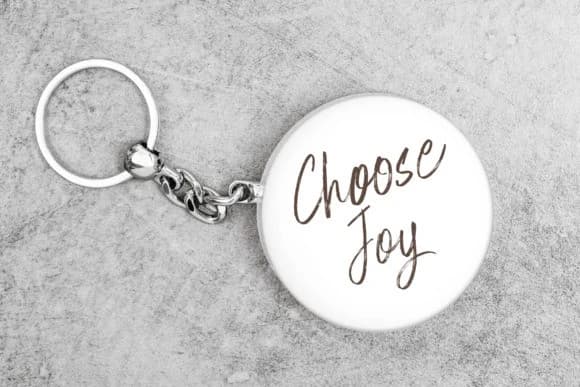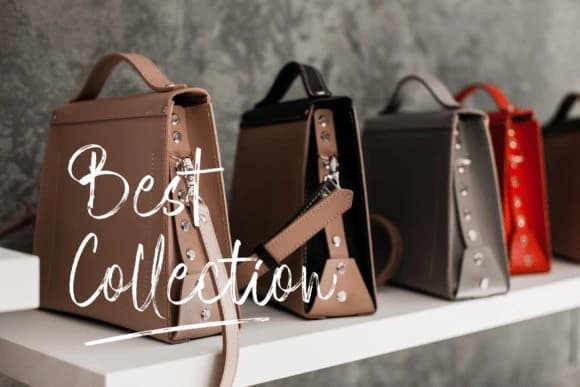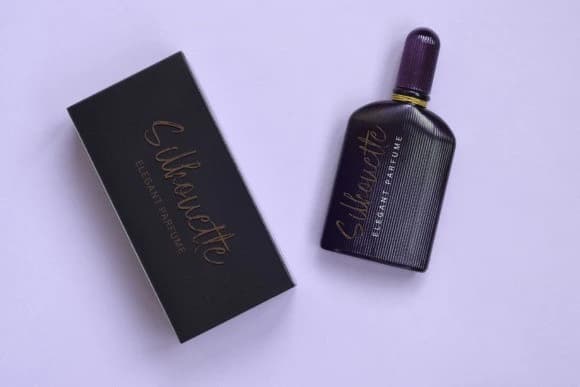
Rettabelle Brush Yazı Tipi
Rettabelle Font – zarifçe rafine edilmiş bir yazı tipi, doğal fırça yazımının cazibesiyle şekillendirilmiş. Romantik estetiği, büyüleyici düğün davetiyeleri tasarlamak, benzersiz marka kimliği oluşturmak, şık logolar tasarlamak ve sosyal medyada etkileyici içerikler üretmek için idealdir.
Rettabelle Font – zarifçe rafine edilmiş bir yazı tipi, doğal fırça yazı stili çekiciliğiyle şekillendirilmiş. Romantik estetiği, büyüleyici düğün davetiyeleri tasarlamak, farklı marka kimliği oluşturmak, şık logolar tasarlamak ve sosyal medyada etkileyici içerikler üretmek için idealdir.